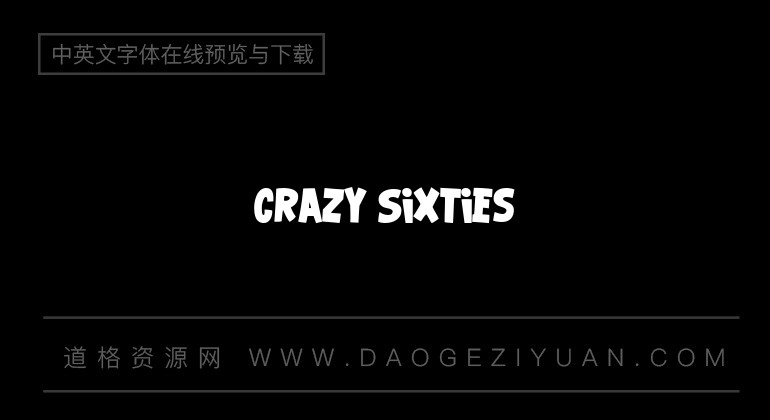
Crazy Sixties 是一种装饰性的手写风格字体,它的设计灵感来自于 60 年代的时尚和艺术风格。这种字体具有强烈的视觉冲击力和个性化的特点,非常适合用于海报设计、音乐封面、宣传册和其他具有艺术性质的设计项目中。 Crazy Sixties 字体的特点包括: 1. 带有强烈的手写风格,每个字母都带有明显的笔画和连接线。 2. 字母的形状和大小都有所不同,形成了一种富有节奏感的排版效果。 3. 字母之间的间距很小,使得整个字体看起来更加紧凑和有活力。 4. 字母的轮廓线条非常粗,强调了字母的形状和视觉效果。 总体来说,Crazy Sixties 字体是一种非常具有艺术性和装饰性的字体,适合用于需要突出个性和视觉效果的设计项目中。内容介绍
Crazy Sixties是一款非常不错的手写艺术字体,具有很好的视觉感,适合于文化类的宣传设计、商业类品牌的广告和产品包装设计以及个性化文字排版等较多场景。